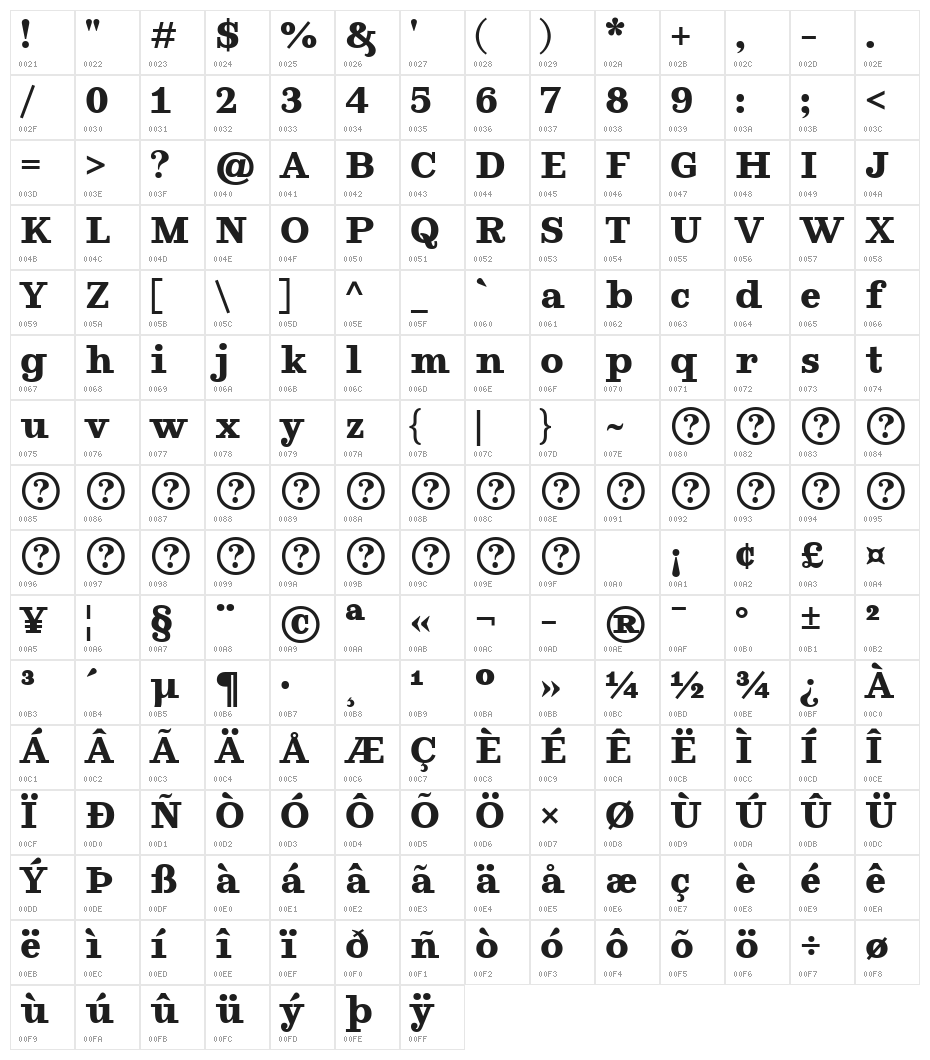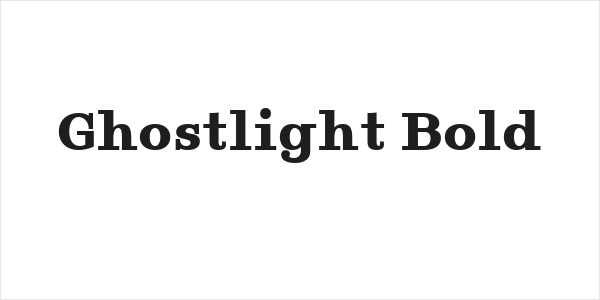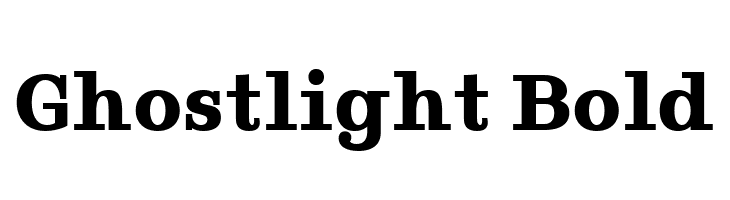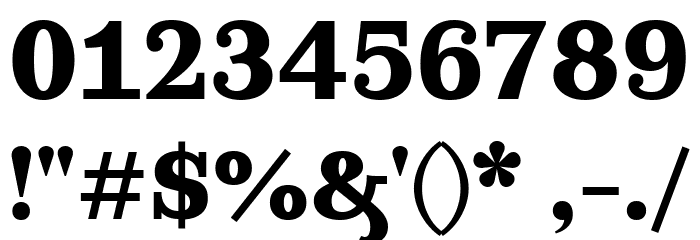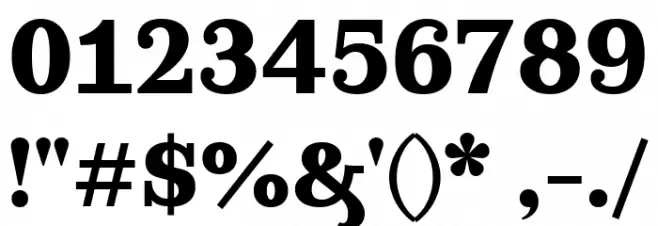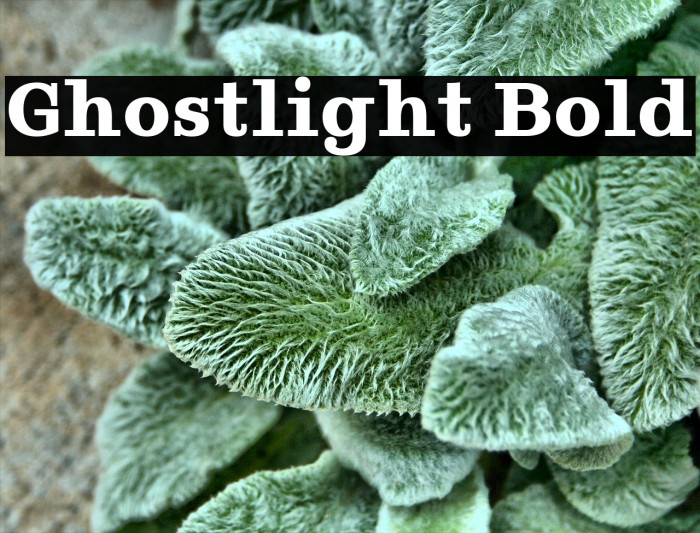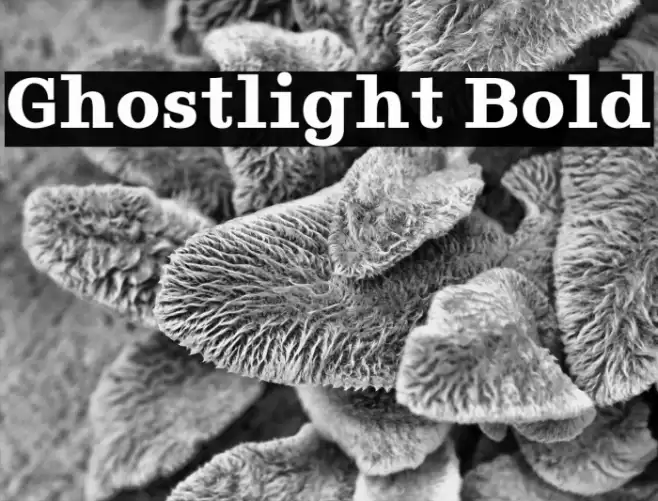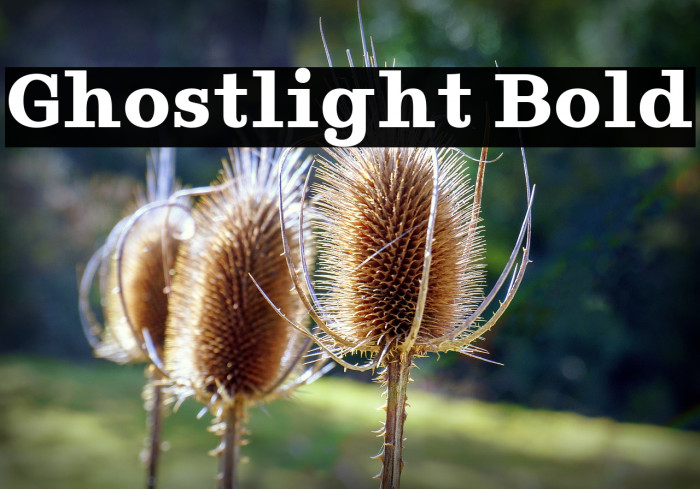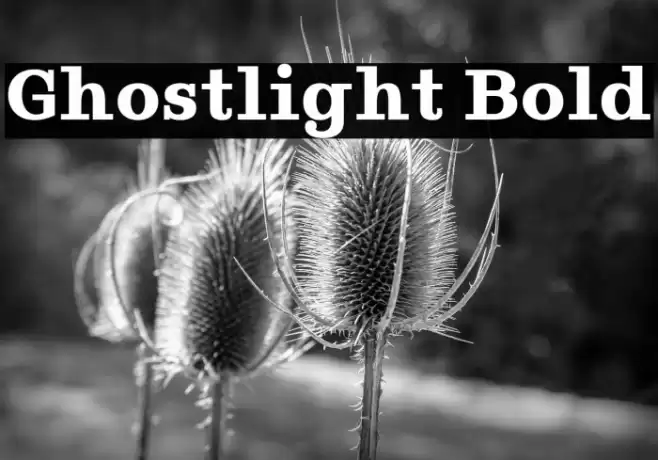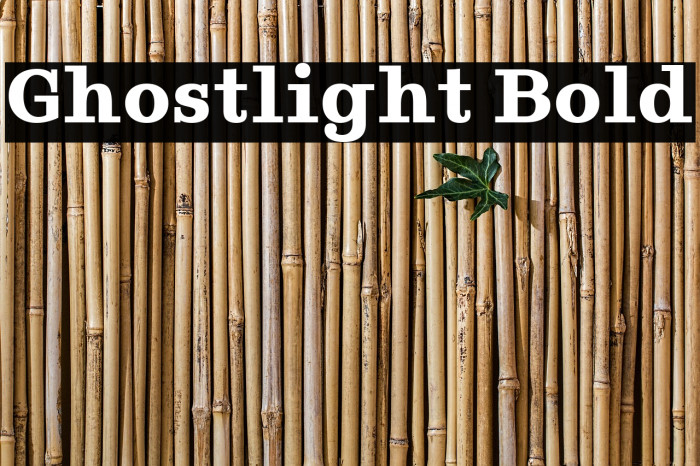
Ghostlight Bold Font
| Projets proposés | This font is perfect for branding, editorial design, posters, and any project requiring a strong, authoritative typeface. |